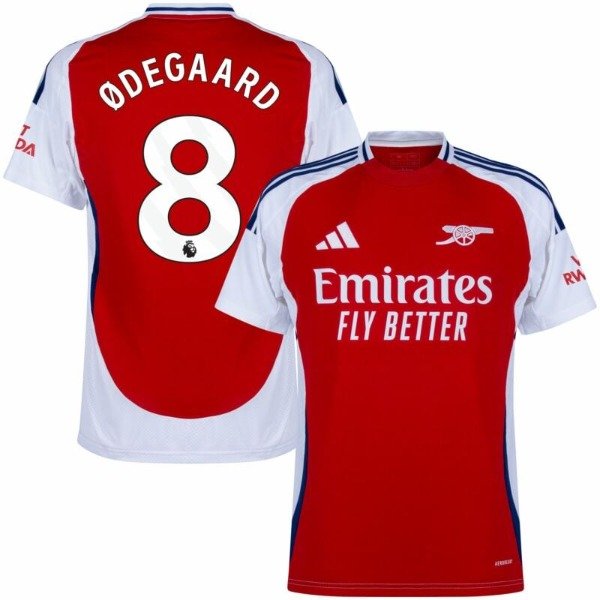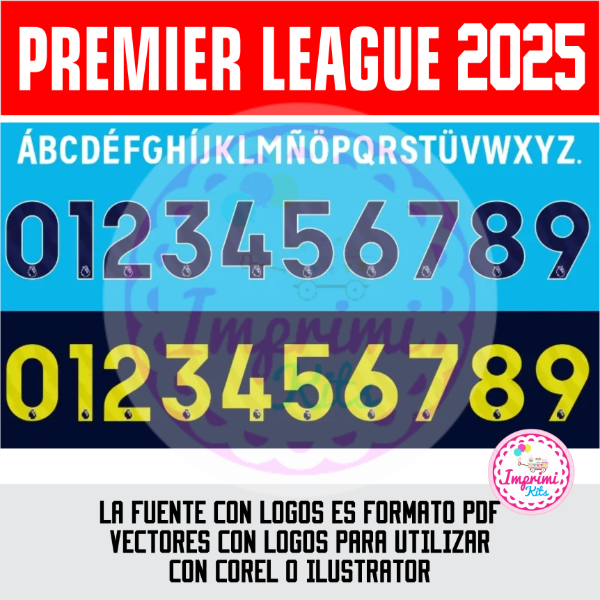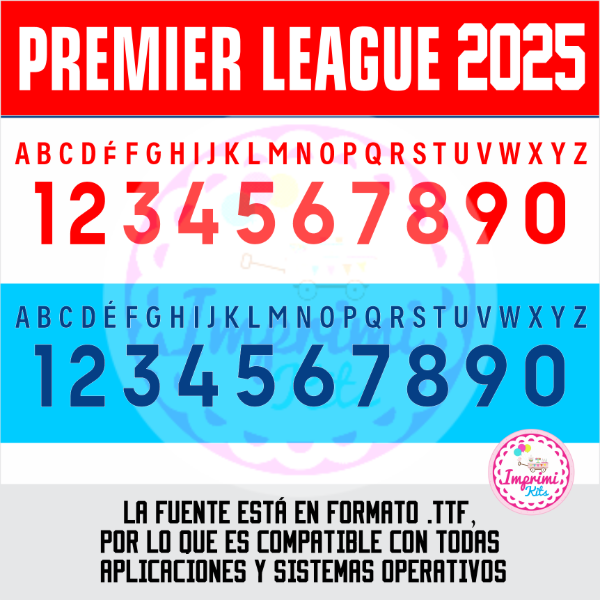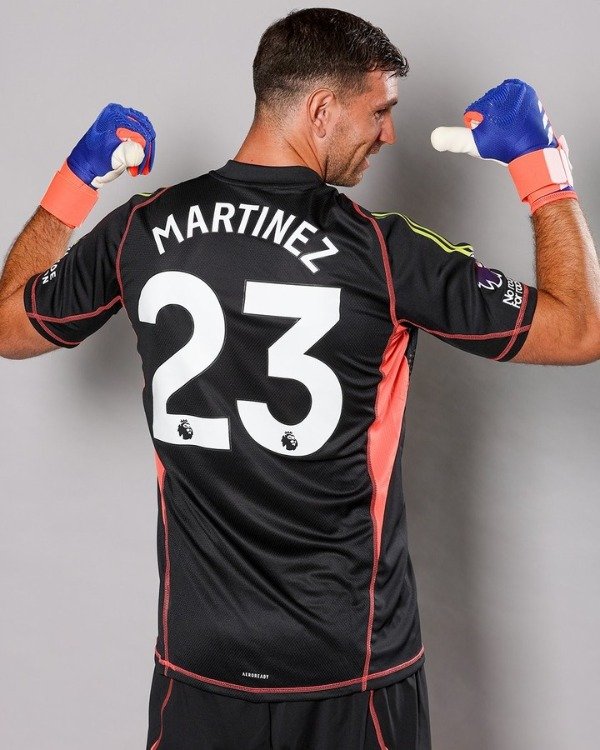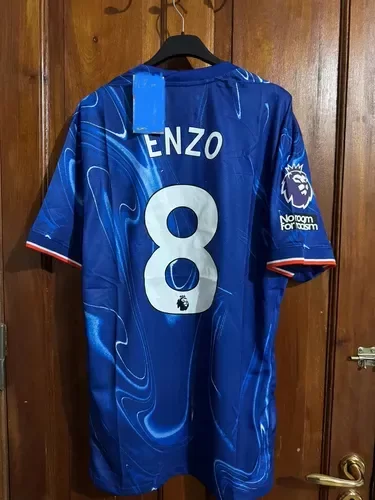
NUEVA! Tipografía Números Fuente Camisetas 2025 EQUIPOS PREMIER LEAGUE
Tipografía Números Fuente 2025 NUEVAS EQUIPACIÓNES
Los vectores de numeros dorsales incluyen detalles y el logo oficial en el numero
Realizá todo tipo de creaciones con la tipografía utilizada actualmente en el club